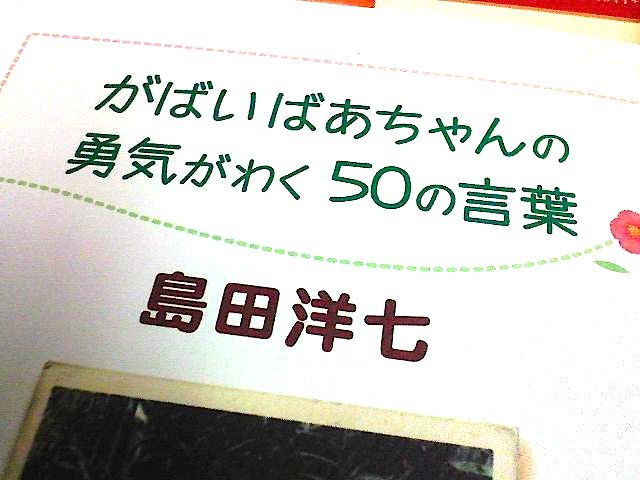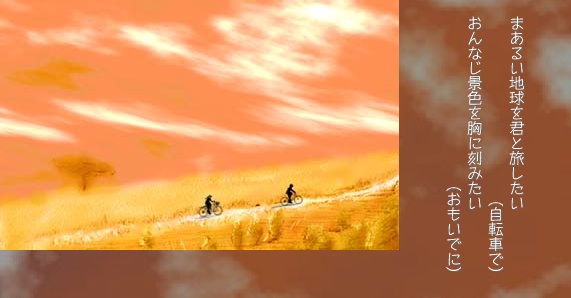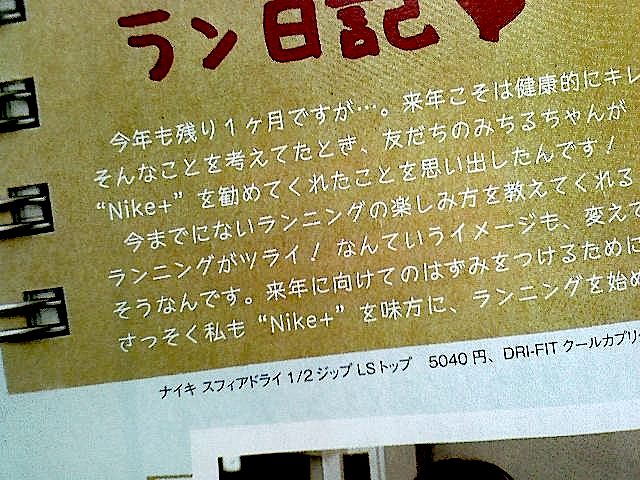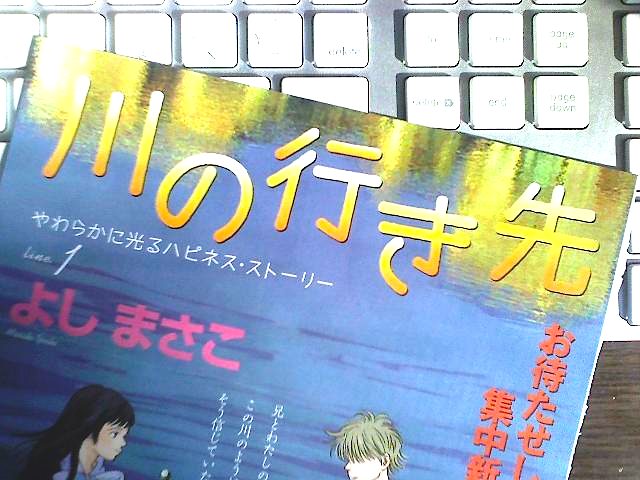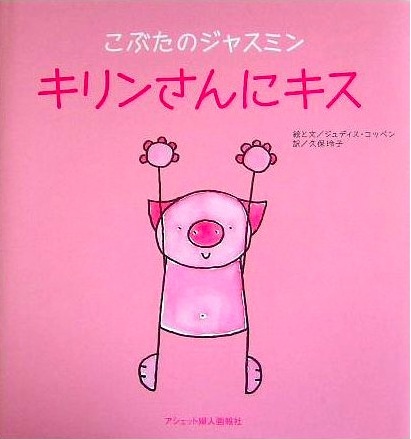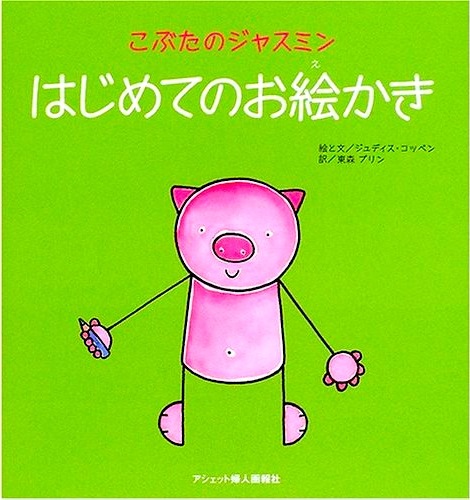
グラフィックデザイナー歴約10年ですが、
見た瞬間こんなに胸が騒いだ書体は今までにはありませんでした。
無料ダウンロード分で個人的なものを楽しんでおりますが、
やはり、不便です。というより、「セプテンバー」が大好きなのです。
この文字ができるまでのプロセスもとても興味深かったです。
わたしもいつか自分の書体を作ってみたい、と大それた事を夢見つつ、、、
この文字を誕生させてくださり、どうもありがとうございました!
いつか、よーこさんも書体を作り始めるのでしょうね。
大変な部分もありますけど、出来上がったときの喜びも大きいですよ。
こんにちは、墨東99のダウンロードをしていてこちらの掲示板に初めて気づきました。
いささか古いのですが、2006年、2007年に制作した大学のパンフレットでセプテンバーを使わせて頂きましたのでご報告させて頂きます。
最初はごく普通のフォントを当てていたのですが、二人がしゃべっている風に構成していたため、ふと手書き風の書体…と思いセプテンバーに変えてみたところ、しっくりと来ました。
今年は学部の構成が変わってしまったため残念ながらこのページが削られてしまいましたが、先生方にも大変好評でした。
使っていた3ページをキャプチャしましたがファイルサイズの関係で小さくなってしまいすみません。
この書体、メジャーなフォントベンダーから販売されていないせいなのか、使用例を見る機会は少ないです。
着実に売れてはいるんですけどね。太いウエィトのものが無いから、見出しなど強い表現に使えない…という事情もあるのでしょう…。
いま制作中のD書体が終ったら、太いものを作る予定でいますので、皆さん待っててくださいね。
SF短編小説らしい  さとうゆたか  2008年6月23日(月) 17:31
先日みつけました。
書 名:ユメウツツ模型店
著 者:山石洋史
出版社:文芸社
こんな本の表紙にも  さとうゆたか  2008年3月21日(金) 16:53
著者:鷲田小彌太
出版社:こう書房
さかなのうた  さとうゆたか  2008年3月17日(月) 17:14
大反響を巻き起こしている音楽アニメの字幕に使われています。
↓
http://jp.youtube.com/watch?v=u7-YmyMSEhI&fmt=18
何年か前の本ですが  こういち  2008年3月2日(日) 20:25
こんにちは。セプテンバー愛用しております。
日記で「商業的に使われる例は少ない」とおっしゃっていましたので、個人的に気に入っていた使用例を。リュウミンとのコントラストが面白いなと思いました。
1文字のみのシンボル的な扱い。こういう使い方もあるのですね。
この書体のこと、気にかけてくれてありがとうございます。
作者にとっては、どの書体も自分の手で紡ぎだしたものですので、役に立っている姿を見るのは、成長した子供を眺めるような感じで、どんな形でも嬉しいものです。
セプテンバーの教漢を使わせていただいているのですが、今回ふと購入を思い立ち、
ロットリングペンで書かれた文字の再現と知りました。
学生のころ、ロットリングペンでニュースを書いていて、まさにこのような字を理想としていました。
もうロットリングを使うことはなくなりましたね…。
用途によっては、英字部分がプロポーショナルのものにするか、等幅にするかも重要ですね。
こぶたのジャスミン  さとうゆたか  2008年2月29日(金) 21:02
絵本の表紙です。
作者:Judith Koppens、久保玲子
出版社:アシェット婦人画報社
こちらも同じシリーズです。
作者:Judith Koppens、東森プリン
出版社:アシェット婦人画報社
漫画のタイトル  さとうゆたか  2007年12月31日(月) 10:12
月刊の女性向け漫画雑誌に連載が始まったばかり。
扉のページです。ちょっと太く加工されています。
題名「川の行き先」と、その下の小さい文字もセプテンバーですね。
セプテンバーによしのやの「吉」(土・口)はあるのでしょうか?